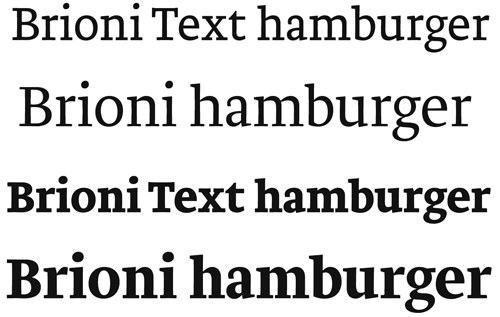
Brioni, diseñada por Nikola Djurek, es la primera familia tipográfica lanzada por la fundición digital Typotheque, que no ha sido diseñada por Johanna o Peter Bil’ak. Nikola ha sido colaborador de esta pequeña empresa con sede en La Haya (Países Bajos), desde que completó sus estudios en el Máster de Tipografía en el Type and Media de la Royal Academy of Arts, primero como ayudante en los temas de producción tipográfica y más adelante como coautor de las fuentes Fedra Serif Display, Greta Display y Grande.
Brioni se desarrolla a partir de la experimentación práctica con la pluma de punta ancha, donde realizando sutiles variaciones de trazo en la práctica del dibujo, se consigue un resultado híbrido con diferentes influencias caligráficas que sitúan a esta tipografía (sobre todo la versión Text) cerca de los modelos tipográficos típicos de las fuentes Sans serif. Este mismo concepto se ha trasladado posteriormente a una versión más contrastada para una fuente de estilo más convencional. El resultado es un familia tipográfica altamente funcional de fácil legibilidad y que invita a la lectura.
La familia Brioni se presenta en dos versiones: la primera es Brioni Text, una robusta slab serif para utilización en texto a cualquier tamaño, pero especialmente indicada para impresiones de lujo. Sus proporciones y su color la hacen ideal para texto seguido, incluso en condiciones difíciles (tanto de lectura como de impresión) como por ejemplo los periódicos.
La segunda versión se denomina simplemente Brioni, una fuente de alto contraste entre sus trazos que la hace indicada para su utilización tanto en libros como revistas. Cada una de estas dos versiones se compone de cuatro pesos, con sus respectivas itálicas, versalitas y versalitas itálica.